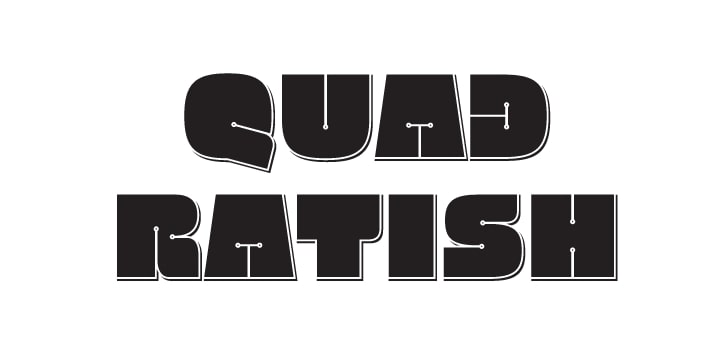
Шрифт Quadratish
это выразительный дизайнерский гротеск с ультражирным начертанием (ultrablack), созданный студией Gaslight. Шрифт отличается уникальным характером: он сочетает в себе массивные, почти брутальные формы букв с возможностью создания эффекта объема за счет комбинации сплошного и контурного стилей. Адаптирован для набора на кириллице и латинице, что делает его универсальным инструментом для современных проектов. Благодаря своей смелой геометрии и высокой читаемости в крупных размерах, он идеально подходит для акцидентных задач, где нужно мгновенно привлечь внимание. Если вы ищете шрифт с характером, **Quadratish скачать бесплатно** можно на нашем сайте для ознакомления или личного использования (лицензию уточняйте)